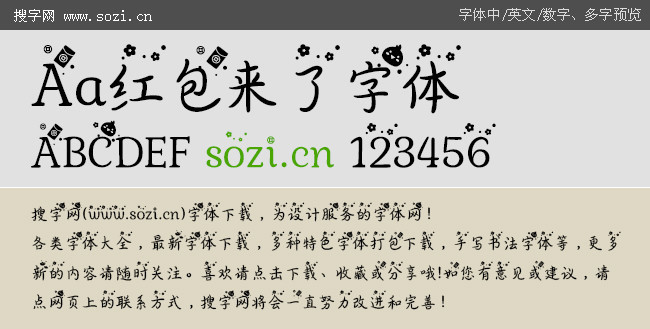
Aa紅包來(lái)了字體
搜字網(wǎng)給大家提供一款A(yù)a紅包來(lái)了字體中文卡通字體下載,這是一款手寫(xiě)風(fēng)格的卡通字體,充滿(mǎn)童趣,非常可愛(ài),適合手機(jī)顯示使用、卡通畫(huà)冊(cè)、兒童用品宣傳廣告等應(yīng)用(此字體為個(gè)人非商用版,如需商用請(qǐng)聯(lián)系作者購(gòu)買(mǎi)版權(quán))。